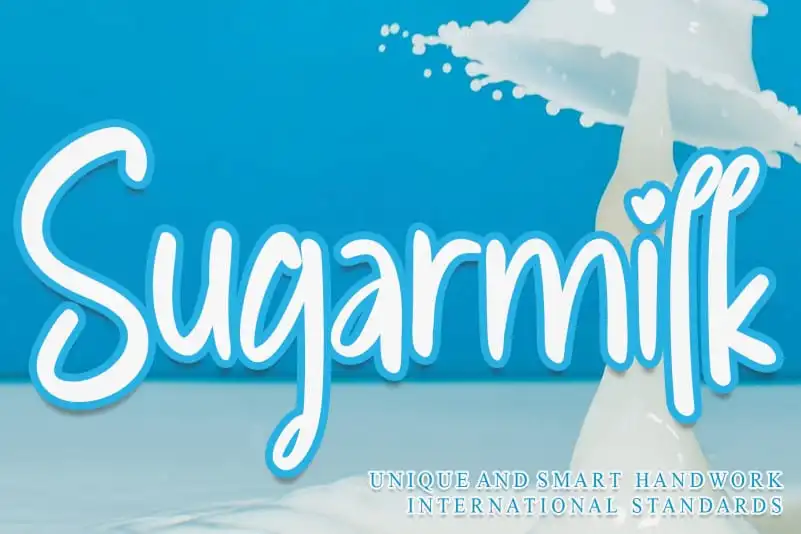
Sugarmilk Brush Font
A Sugarmilk Brush Font é uma seleção única de letras frondosas e suaves, perfeitas para quem procura um touch criativo para suas criações digitais. Lançada pela designer creativletter, essa fonte apresenta traços leves e curvos que destacam a delicadeza da escrita à mão livre. Com uma categoria especializada em Fonts de Letras a Esmagado, ela oferece uma experiência única para quem busca personalizar seus projetos com um toque mais íntimo e detalhado. Seja para criar cartões de aniversário customizados ou gráficos de design gráfico, essa fonte se destaca por sua capacidade de dar vida a qualquer texto que seja tratado com ela, tornando cada projeto personalizado ainda mais especial.